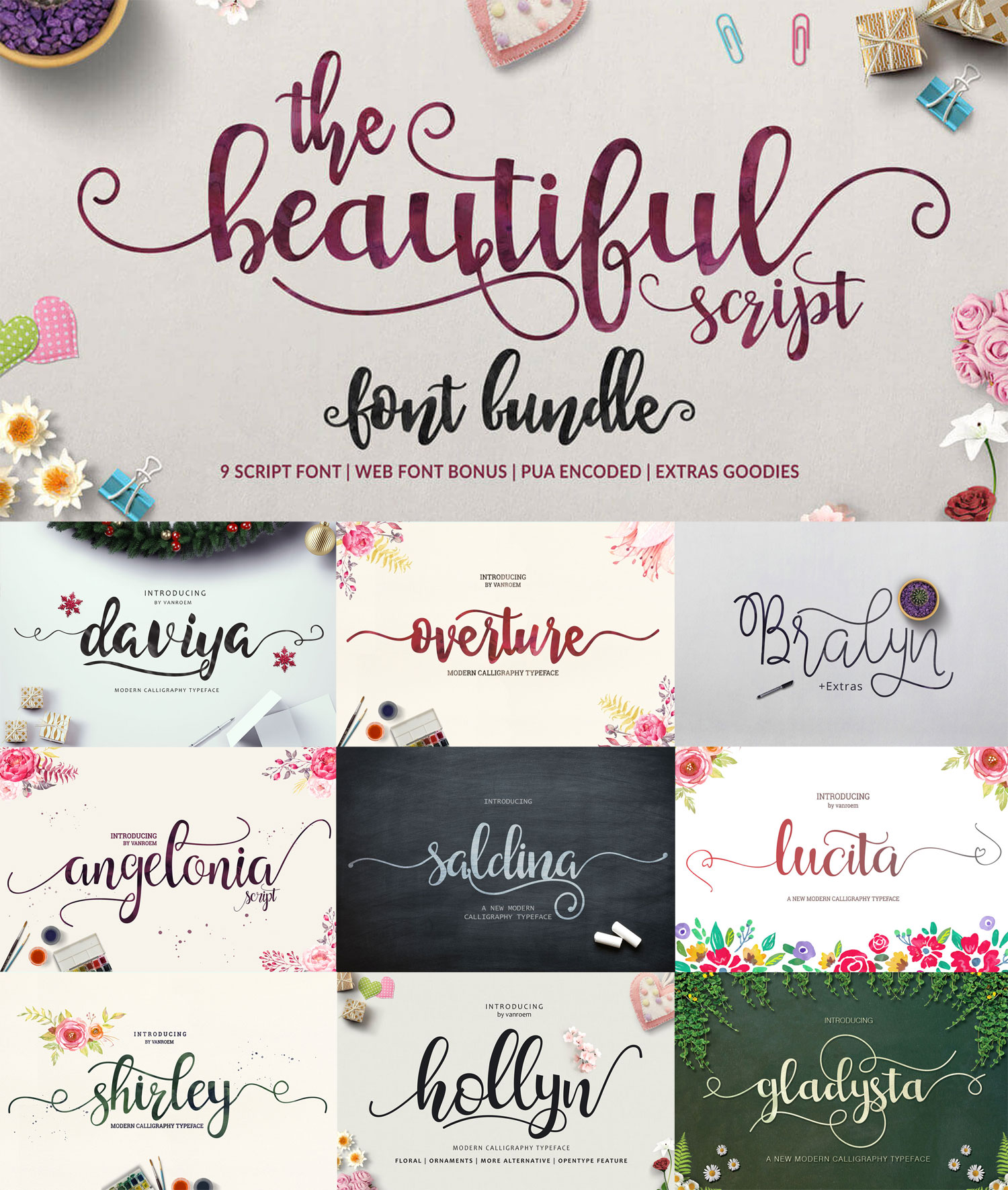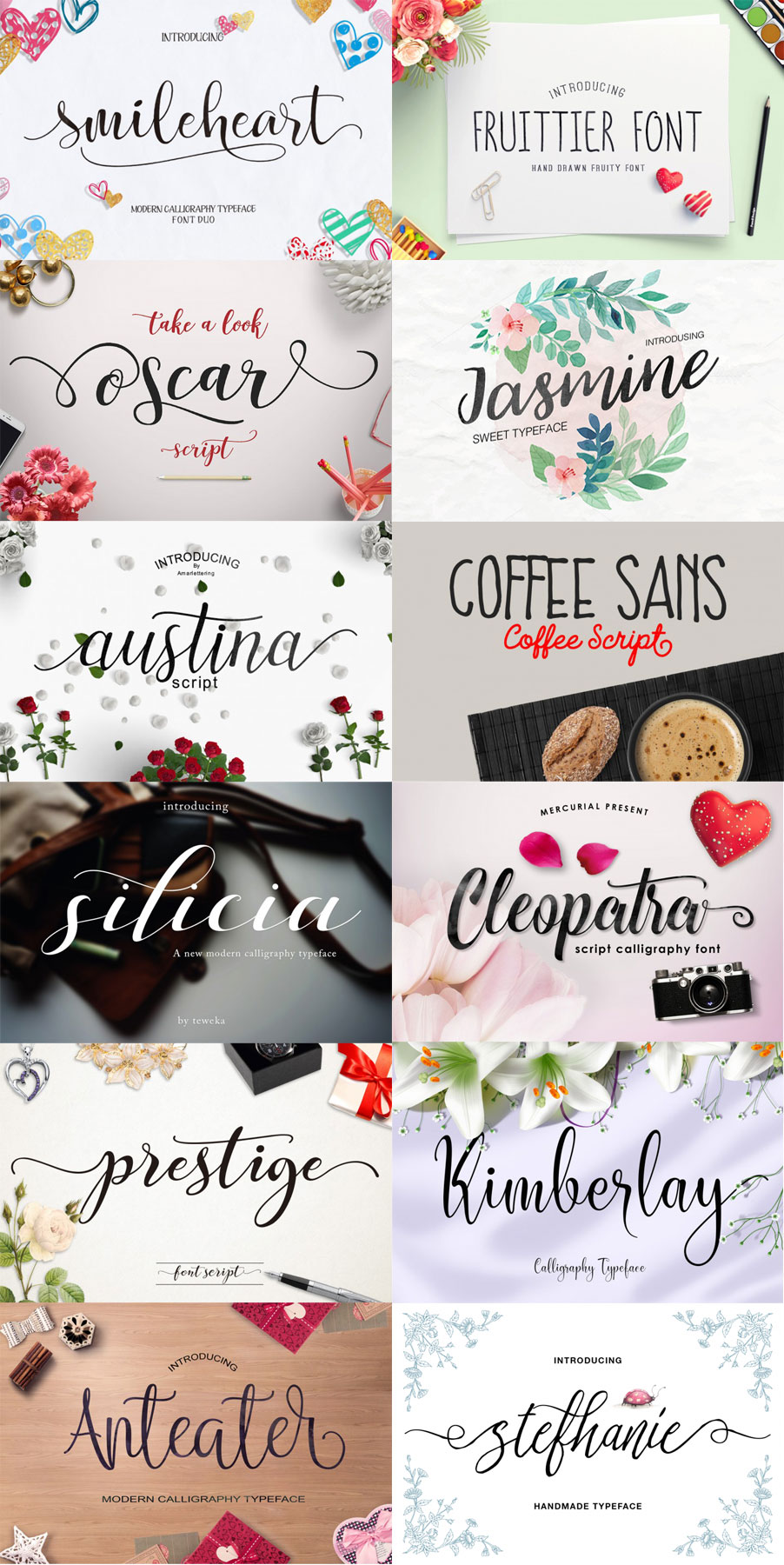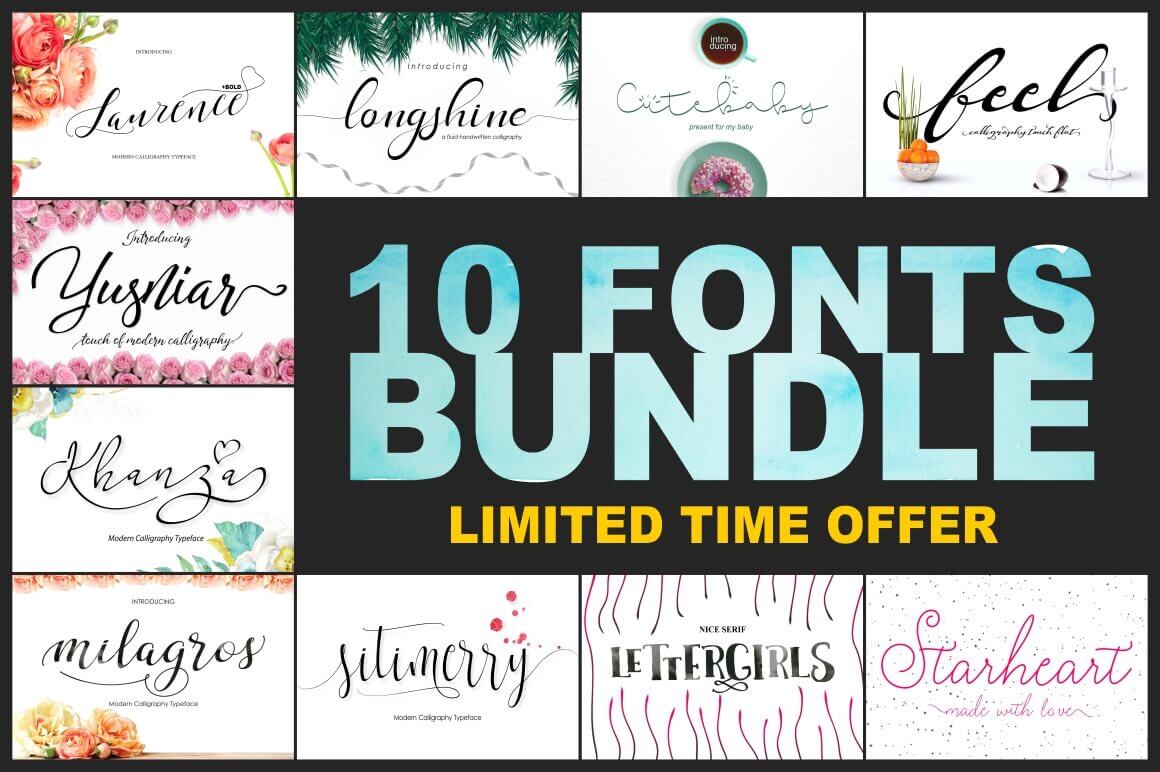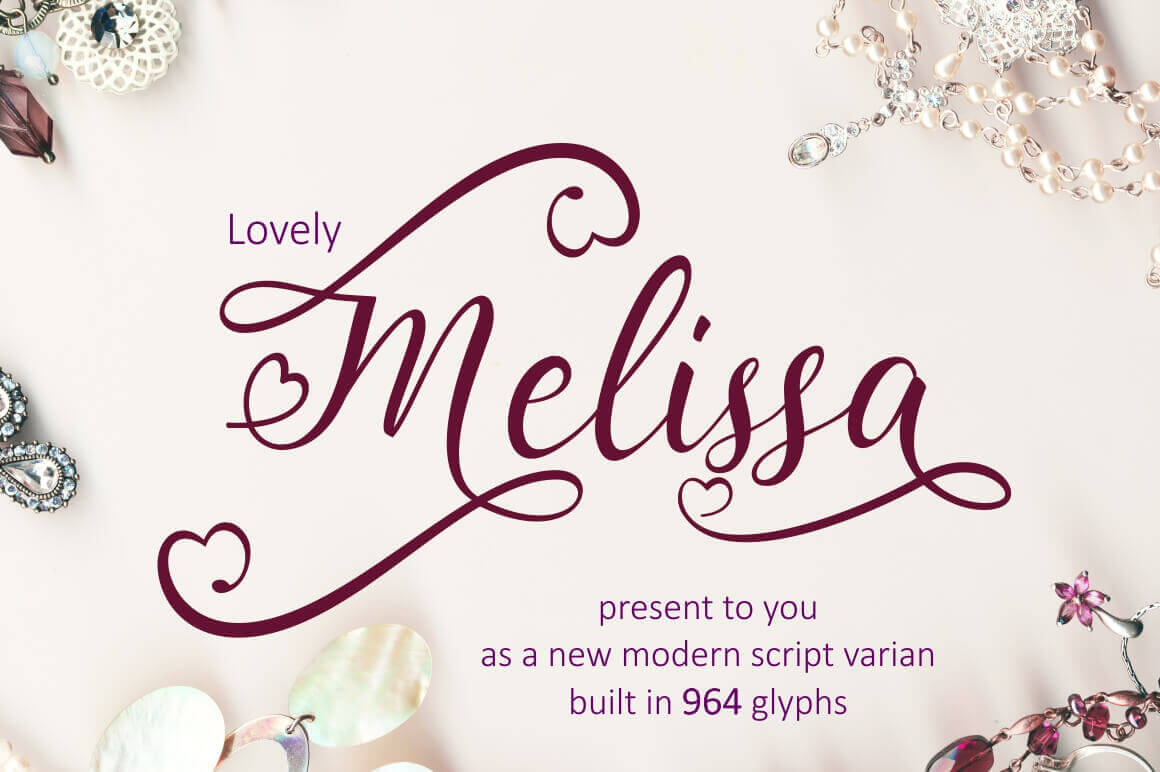
[шрифт] Набор шрифтов для приглашений, постеров
Шрифт Lovely Melissa
Содержит 964 глифов. Идеально подходит для создания приглашений, печати на футболках, визиток.
Набор из 9 шрифтов
Angelonia
Saldina Script
Gladysta
Lucita
Bralyn
Hollyn
Overture
Shirley
Daviya
Набор из 10 шрифтов
Cute Baby Script
Feel Script
Yusniar Script
Khanza Script
Laurence Script
Letter Girls Script
LongShine Script
Milagros Script
Sitimerry Script
Starheart Script
10 красивых шрифтов